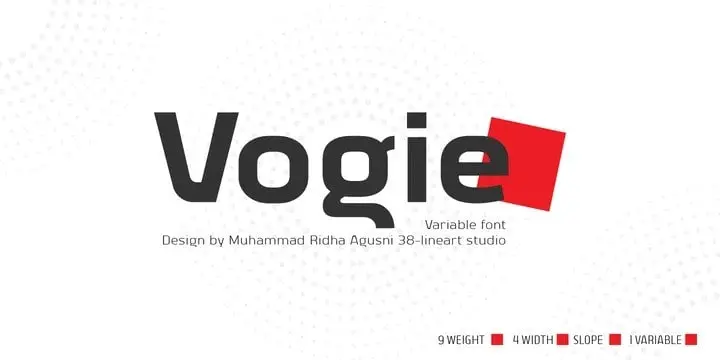
Vogie Sans Serif Font – Fonte Grátis
Vogie Sans Serif Font
Vogie Sans Serif Font é uma tipografia moderna e estilizada com detalhes únicos, projetada pelo designer 38-lineart no site de crowdsourcing 99designs. Suas sutilezas tornam este tipo de escrita perfeitamente adequado para títulos, headlines ou textos mais curtos, garantindo um visual chamativo e elegante. Com quatro diferentes larguras, nove pesos e disponível tanto em sua versão regular quanto obliqua, esta fonte incorpora um número impressionante de 62 fontes em uma única variável, tornando-a ainda mais moderna e prática para o uso diário. Suas características fazem dela uma escolha ideal para ambientes desportivos ou ambientações modernas. O fato de Vogie Sans Serif Font ser uma tipografia serif-less garantirá um contraste atraente em qualquer layout gráfico, combinando perfeitamente com textos mais longos e detalhados. A combinação de modernidade e sofisticação oferecida pela 38-lineart torna Vogie uma fonte indispensável para designers buscando incorporar um toque único ao seu trabalho.